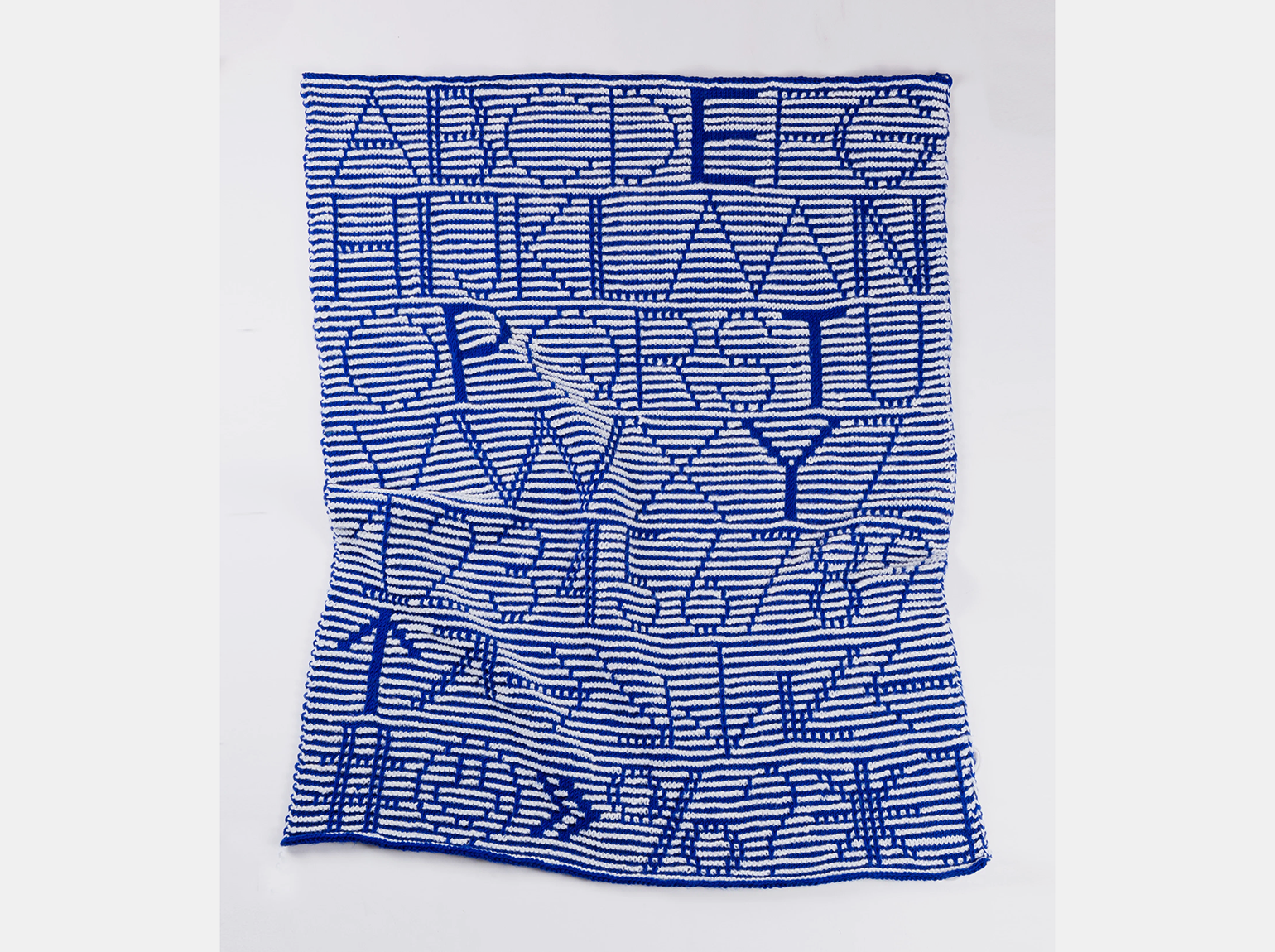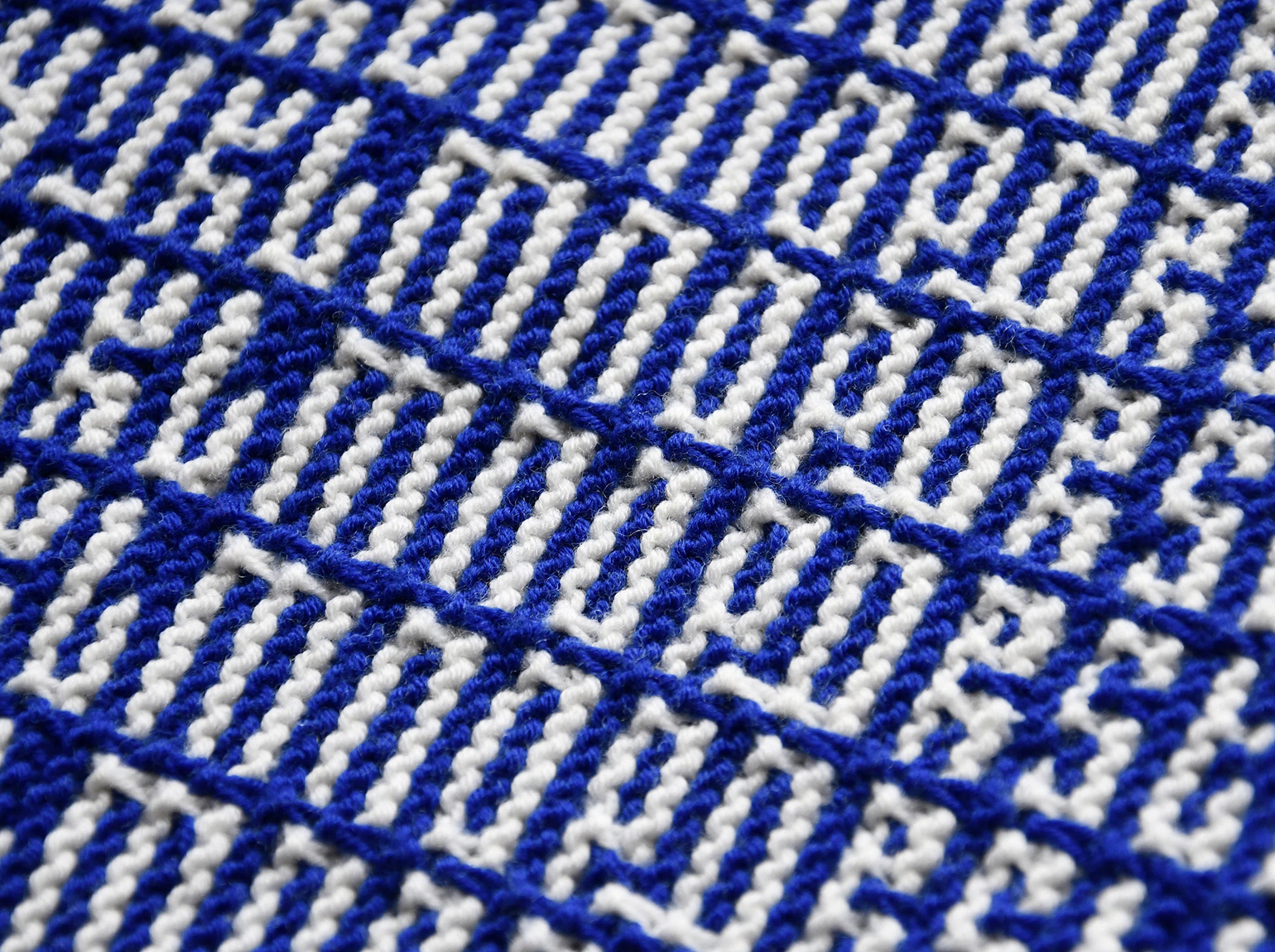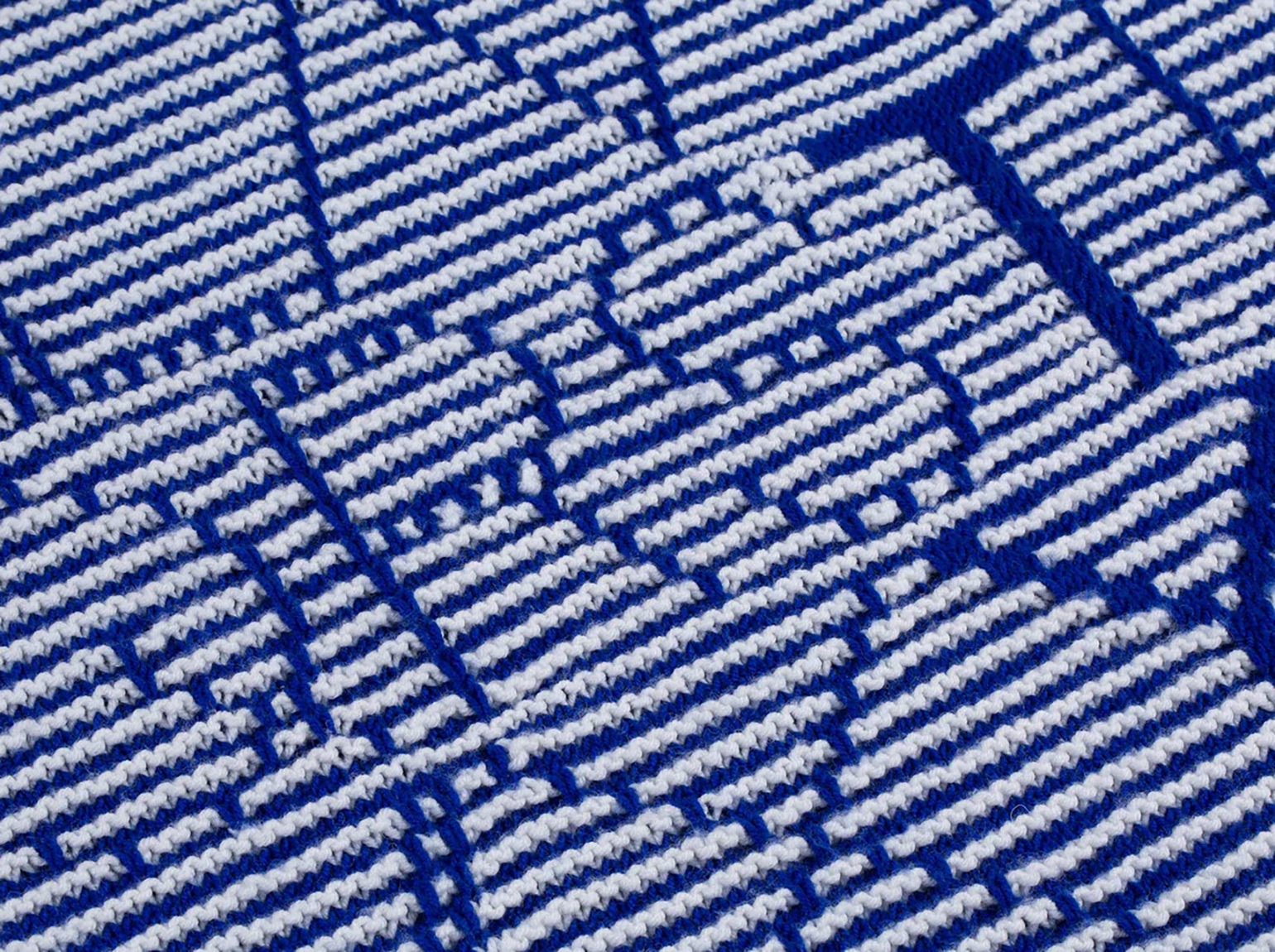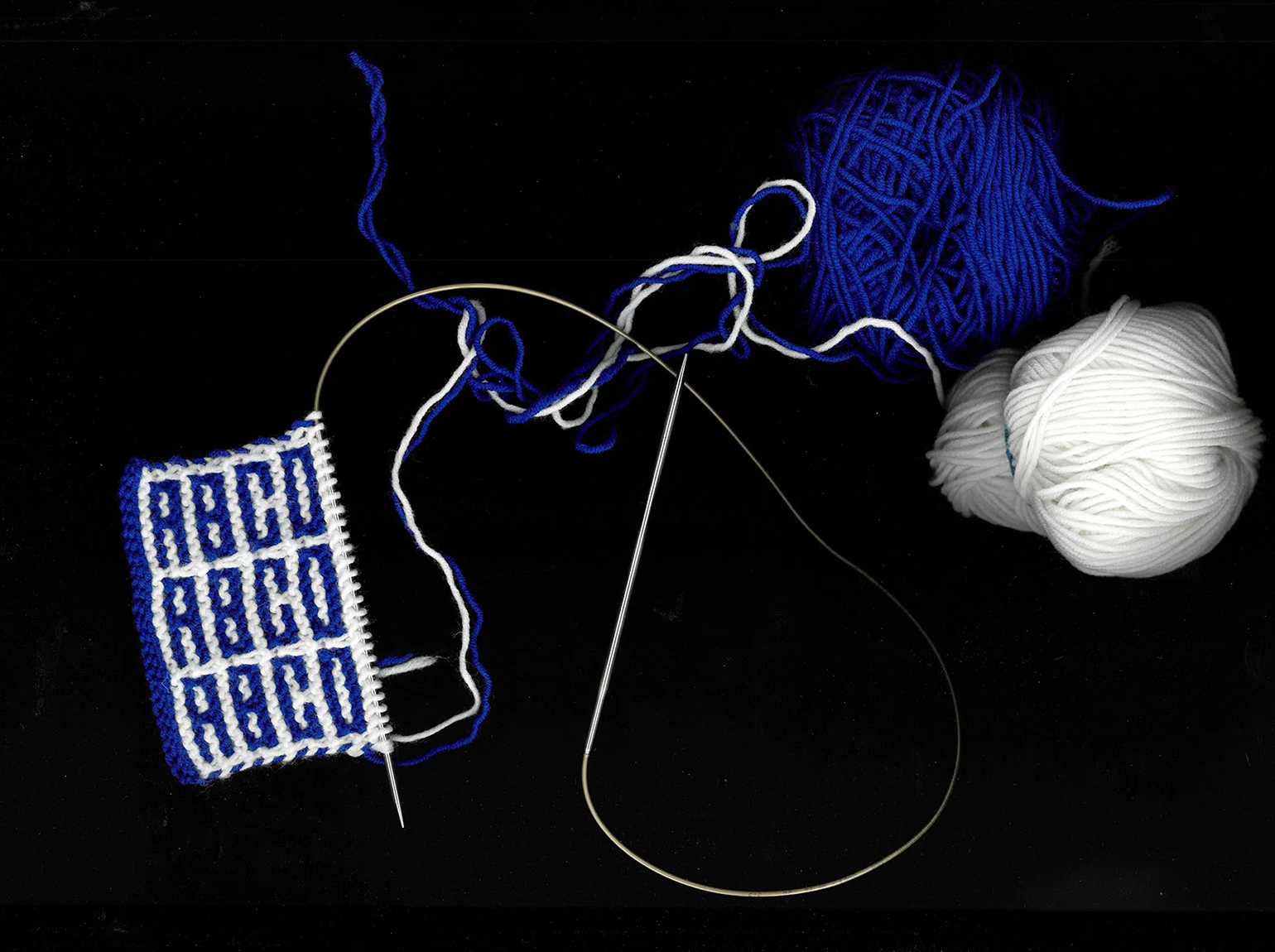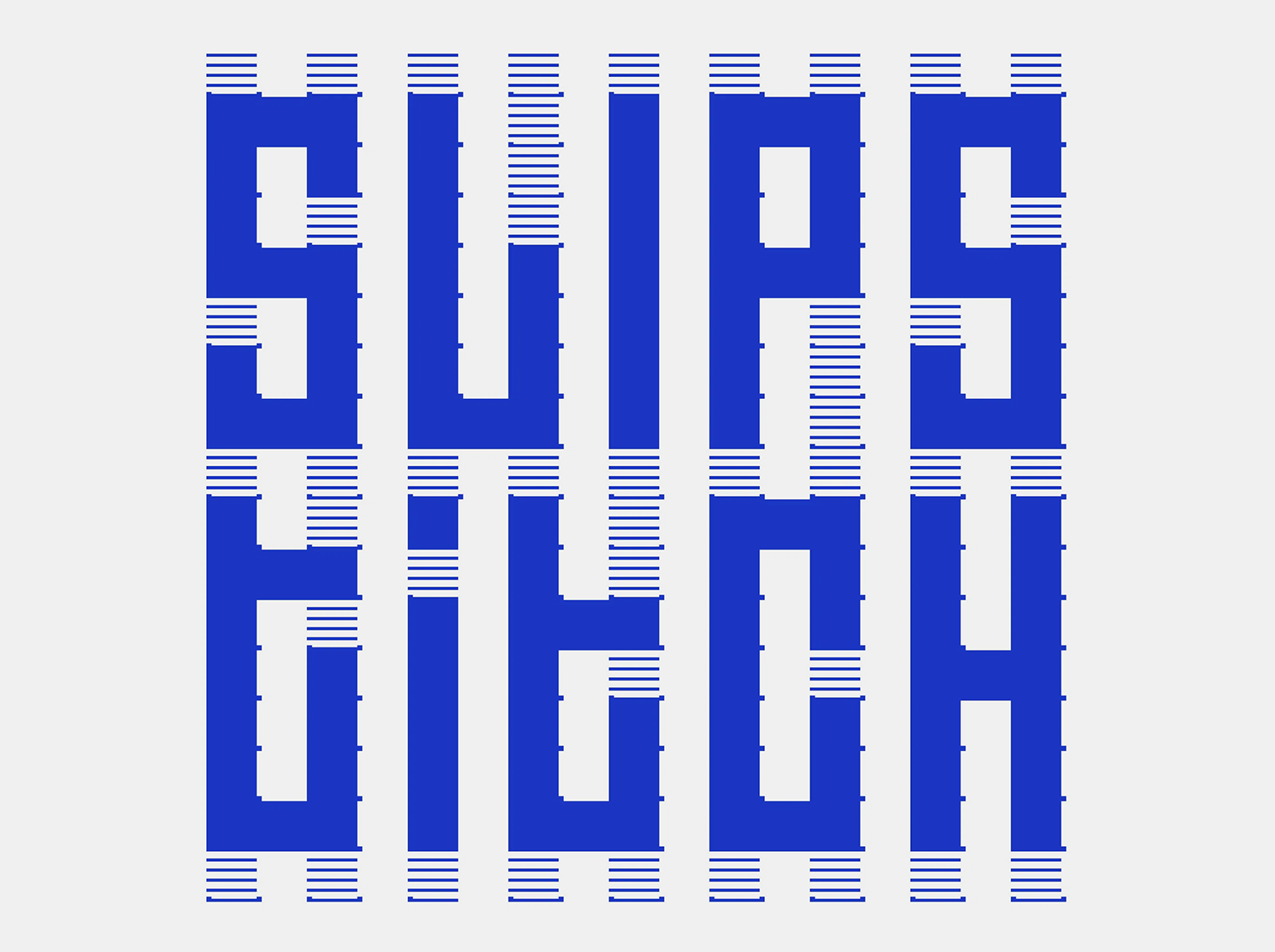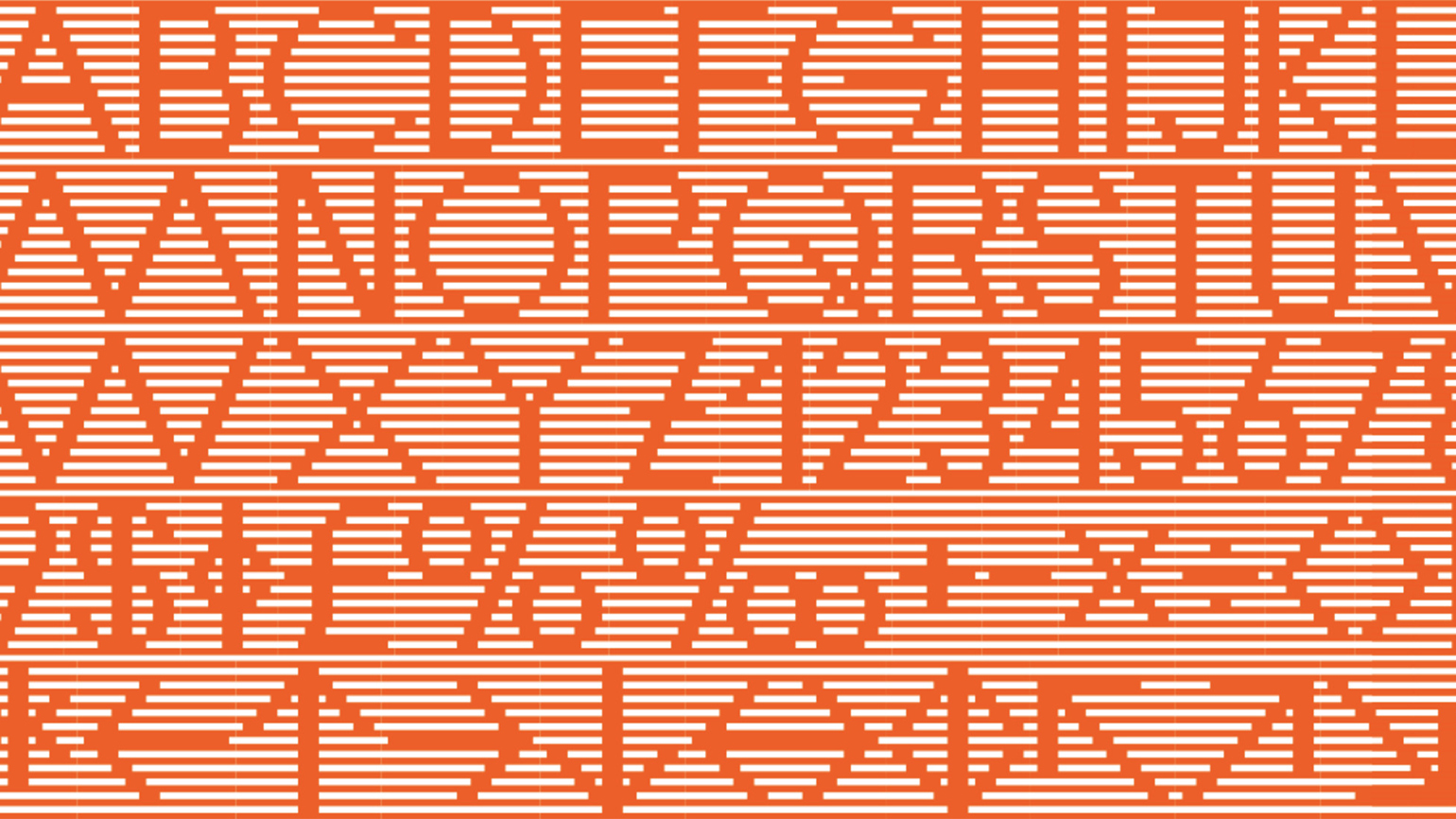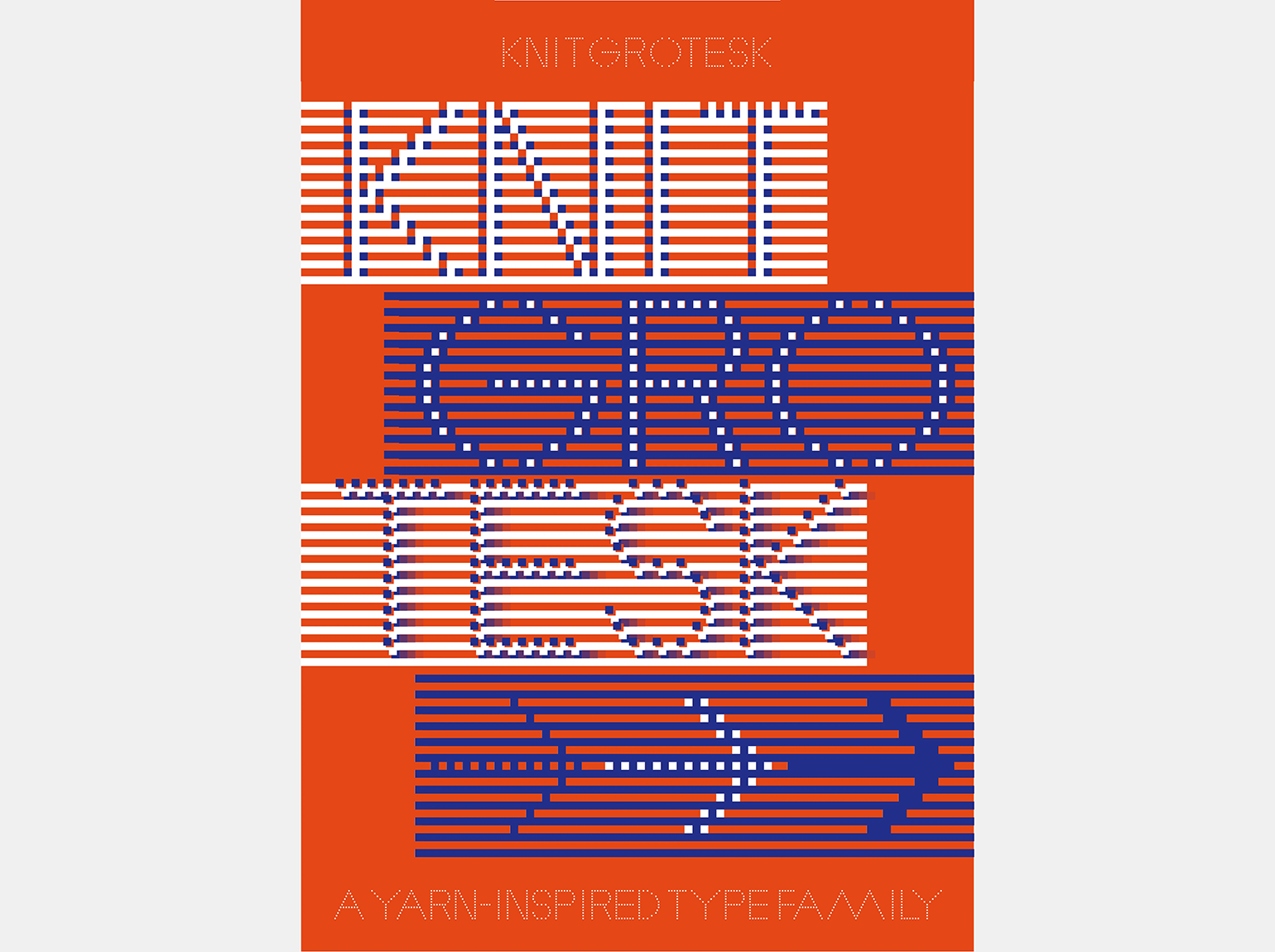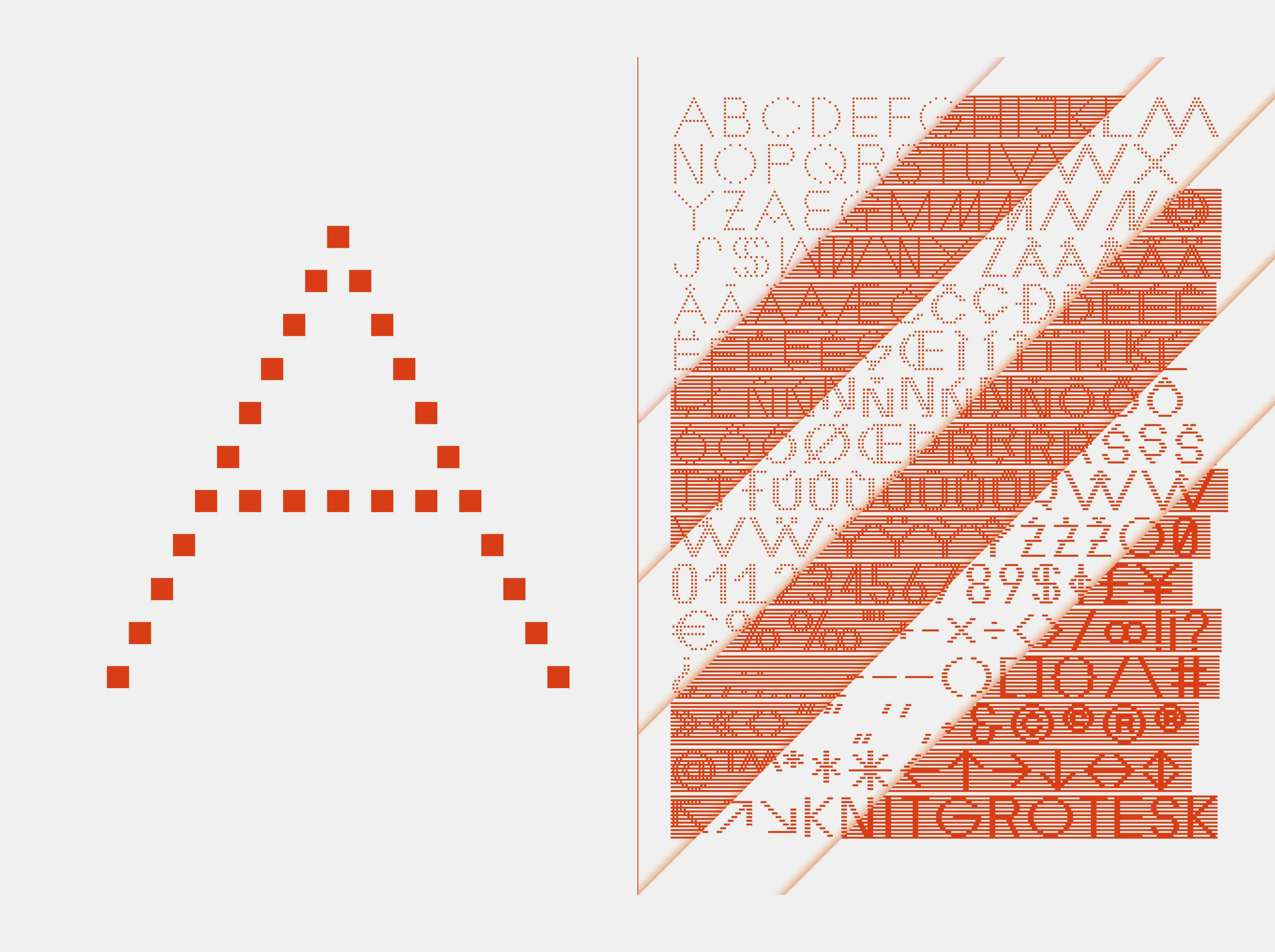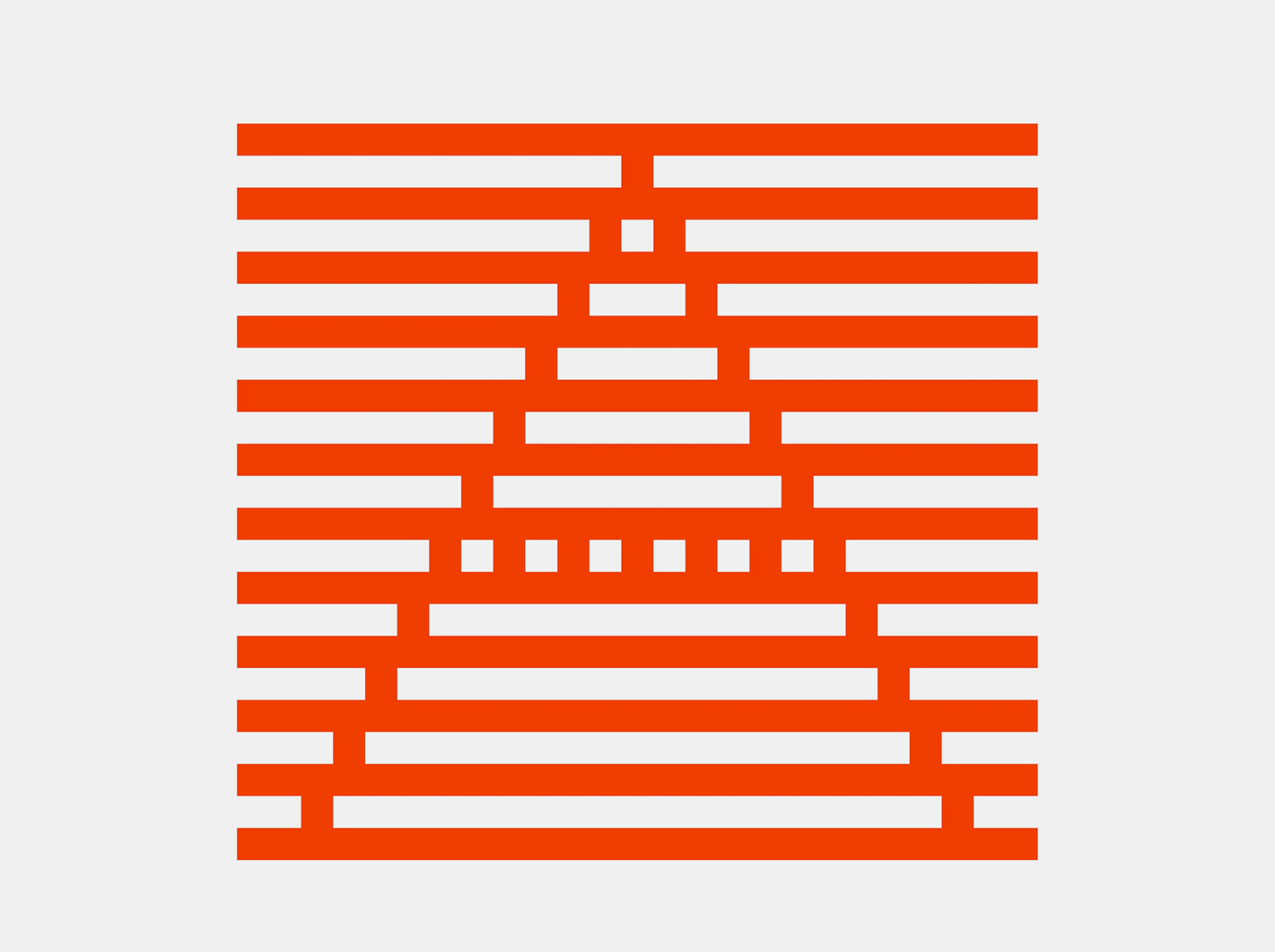
Дизайнер Рюдигер Шлёмер создал шрифты для вязания, которые можно использовать в графическом дизайне
Возможности текстиля ему открыл проект по созданию шарфов для футбольных фанатов.
Рюдигер Шлёмер обожает вязать слова. При этом он признаёт, что в этом есть некоторые трудно преодолимые препятствия. Это кажется простым: один пиксель равен одной петельке. Пока не окажется, что петля больше похожа не на квадрат, а на букву V.
Рюдигер Шлёмер говорит, что «печатать шерстью — это всё равно что уличному художнику строить стену, пока он на ней рисует».
В 2023 году Рюдигер Шлёмер выпустил свой первый шрифт для ручного вязания Knit Grotesk. Его опубликовало издательство Nouvelle Noire. Это адаптация Futura — он почерпнул идею, вдохновившись шрифтом с сеткой от Studio Laucke Siebein.
Его можно использовать в цифровом графическом дизайне, для заголовков, для экспериментальных вывесок и плакатов, а также для мозаики или лазерной резки. Knit Grotesk будет работать для любых пиксельных узоров.
Рюдигер Шлёмер разработал его, используя простую технику вязания — соединительный столбик. Самый характерный элемент — вертикальная сетка линий — происходит от чередования двухцветных двойных рядов. Даже когда Knit Grotesk используется на бумаге, Рюдигер Шлёмер считает, что можно каким-то образом почувствовать его текстильное происхождение.
Свой процесс создания прототипов шрифтов Рюдигер называет «кросс-медиальным» — это перемещение между компьютером и креслом для вязания. Он говорит, что это особенно важно для того, чтобы не застрять в логике того или иного средства. Некоторые детали могут отлично смотреться на экране, но при вязании оказываются проблематичными или скучными.
«Например, лоскутное вязание лучше подходит для крупномасштабных пиксельных дизайнов или модульной типографики. Мозаичное вязание имеет много общего с геометрической куфической каллиграфией (это старейшая арабская письменность) и лучше подходит для маленьких букв и повторяющихся узоров», — говорит он.
Дизайнер часто встречал людей, которые скачивают и вяжут его шрифты.
«Одеяло ABC-Blanket, которое я сделал как вязаный образец, вязали много раз, и с учётом того, сколько усилий на это требуется, это очень много для меня значит», — рассказал дизайнер изданию It’s Nice That.